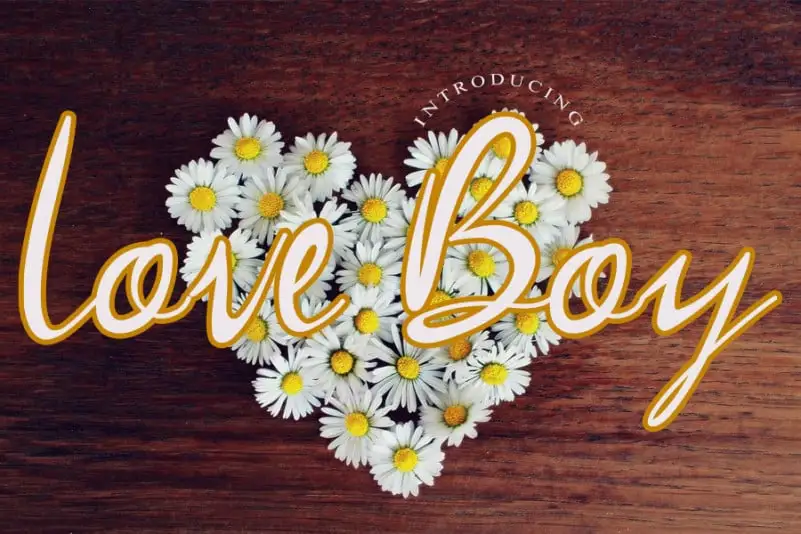
Love Boy Script Font – Download Grátis
A “Love Boy Script Font” é uma elegante e leve fonte cursiva que transmite sentimentos românticos. Ela se destaca não apenas por sua natureza agradável, mas também pela capacidade de adicionar um toque único à sua próxima criação visual. Este design foi projetado para ser perfeito em vários tipos de trabalhos gráficos, incluindo cartões de agradecimento, convites de casamento, cartazes personalizados e até mesmo nas identidades empresariais. A “Love Boy Script Font” é uma opção ideal para quem busca um visual casual e encantador. Ela se torna especialmente atraente quando usada em obras que exigem uma mão escritora natural, como cartões de felicitações personalizados ou logotipos pessoalizados. O designer levincreative criou essa fonte com cuidado para garantir que ela seja acessível e versátil o suficiente para ser usada em uma ampla variedade de projetos gráficos. Se você está procurando por uma fonte perfeita para aquecer seu design, esta é a escolha certa. A “Love Boy Script Font” não apenas oferece um toque romântico, mas também se ajusta com facilidade para diferentes estilos e tamanhos de texto, tornando-a uma ferramenta indispensável em qualquer designer gráfico.